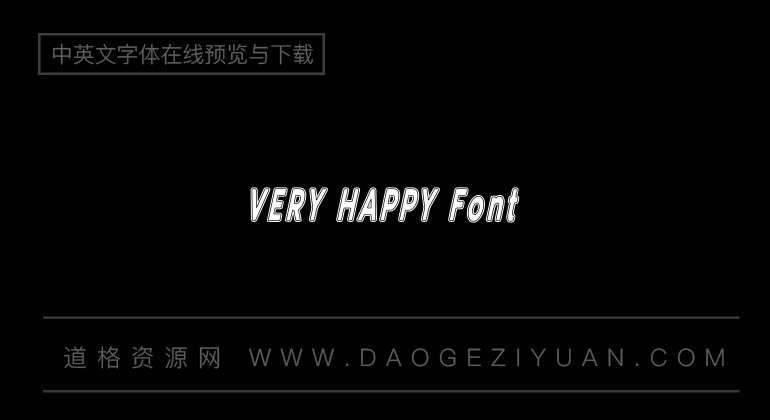
VERY HAPPY Font
抱歉,作为一个 AI 语言模型,我不会以视觉方式展示字体,但是我可以告诉你一些 VERY HAPPY Font 字体的基本信息。 VERY HAPPY Font 是一种手写风格的字体,其中每个字母都具有类似手写的形状和特征。这种字体的设计灵感来源于书信和便条,因此它的字母看起来像是手写在便条纸或信纸上的。 VERY HAPPY Font 很适合用在那些需要传达轻松、幸福、快乐或者是孩子们喜欢的场合,比如儿童书籍封面、生日贺卡、宣传海报等。由于其独特的风格,它也可以在其他场合中使用。
VERY HAPPY Font是一款非常不错的手写艺术字体,具有很好的视觉感,适合于文化类的宣传设计、商业类品牌的广告和产品包装设计以及个性化文字排版等较多场景。